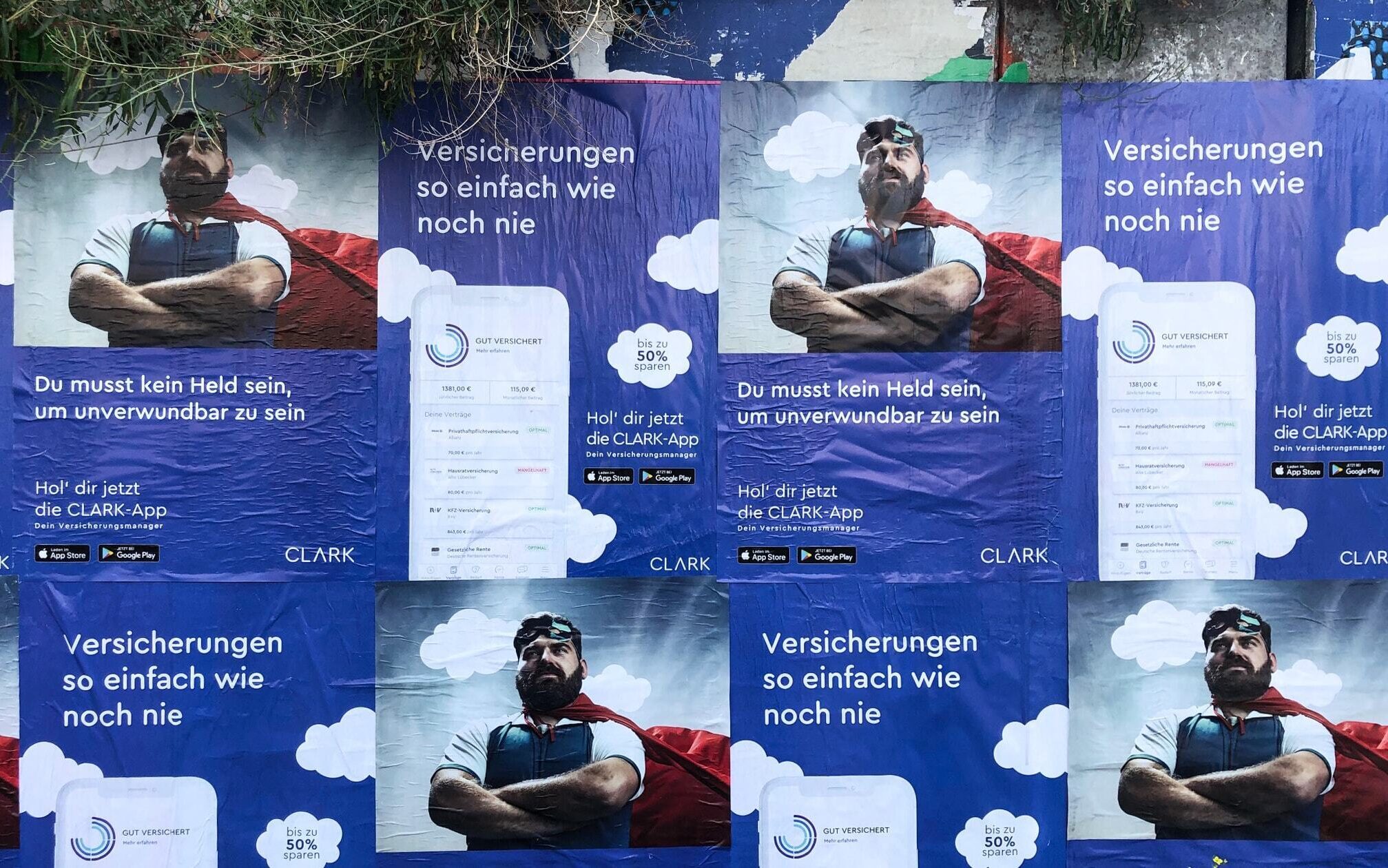
Rundet die Cera Collection ab und bringt Wärme in lateinische, Кириллица und Ελληνικά Sprachen.
Cera Round
CLEAN & FRIENDLY
So gut ausgebaut wie der Rest der Cera Collection, fügt sich die abgerundete Variante Cera Round in die Schriftfamilie ein und verbindet schlichte Eleganz mit einer gewissen Wärme, ergänzt diese jedoch durch weiche und zugleich präzise Formen, welche die Geometrie des kreisrunden Buchstabens O noch einmal verdeutlicht.
In der Tradition von maschinell gefräster Schrift zeichnet sich die Cera Round durch exakt kreisförmige, streng geometrische Strichenden aus. Die Cera Round kombiniert so die mechanisch-technische Geometrie der Cera mit weichen Rundungen, wodurch sie einen sanften, freundlichen Charakter erhält. Eine gute Wahl für Branding und Editorial Design – egal ob für klare High-Tech-Unternehmen oder sanfte Babynahrung.
Durch die Unterstützung der kyrillischen und griechischen Zeichensätze wird die Cera Round zu einem zuverlässigen und einnehmenden Begleiter für internationale Kommunikation. Darüber hinaus ist die große x-Höhe vorteilhaft für Interface Design.
Während der Regular-Schnitt für längere Fließtexte geprüft wurde, bieten die sechs übersichtlichen, aber erkennbar unterschiedlichen Gewichte von Thin bis Black und deren kursiven Stilen, viele Möglichkeiten für die Headline Typografie.
Obgleich die Cera Round als ein Gegenstück der Cera Pro gesehen werden kann, ist sie nicht nur eine simple Version mit abgerundeten Buchstaben. Vielmehr wurden etliche Glyphen sorgfältig neu gezeichnet, um sie an den neuen weichen und dennoch geometrischen Charakter anzupassen. Auch wurde präzise darauf geachtet, die Lesbarkeit in all ihren abgerundeten Ausprägungen zu erhalten. So kann sich die Cera Round als eigenständiges Mitglied innerhalb der Cera Collection behaupten. 2021 haben wir die Familie um die Kursive erweitert, um Cera Round noch ein etwas vielseitiger einsetzbar zu machen.
Ferner enthält die Cera Round viele typografische Extras wie Tabellenziffern, automatische Brüche, nützliche Symbole und Dingbats. Darüber hinaus unterstützt die Cera Round nicht nur die lateinischen Sprachen, sondern beinhaltet auch griechische und kyrillische Zeichensätze mit sprachspezifischen Alternativformen, welche in Zusammenarbeit mit einheimischen Beratern entwickelt wurden. Mit mehr als 900 Glyphen pro Schnitt unterstützt die Schrift auch sprachspezifische Buchstabenvarianten und bietet die passenden OpenType Features.
Die paneuropäische Cera Collection ist von purer Geometrie geprägt und umfasst den Bestseller Cera Pro, ihre platzsparenden Condensed Schnitte, die Schablonenschrift Cera Stencil sowie die handgefertigte Display-Variante Cera Brush und die weiche Cera Round.
Design von
Jakob Runge, Lisa Fischbach
2016, Italics 2021
Irene Vlachou, Ilya Ruderman & Yury Ostromentsky, Christoph Koeberlin
Griechisch: monotonisches Griechisch
Alle enthaltenen OpenType-Funktionen: Alternativen für die Auswahl, Brüche, Durchgestrichene Null, Glyphenz-Zusammensetzung/Zerlegung, Hochgestellt, Kerning, Kontextbedingte Alternativen, Markierung zu Markierung Positionierung, Minuskelziffern, Nenner, Ordinalzeichen, Proportionale Ziffern, Sprachabhängige Formen, Stilistische Alternativen, Stilistisches Set: Alternatives Ξ, Stilistisches Set: Bulgarische kyrillische Alternativen, Stilistisches Set: Dreieckiges ЛлДд, Stilistisches Set: Geometrische Alternativen, Stilistisches Set: Geometrisches a, Stilistisches Set: Geometrisches y, Stilistisches Set: Marcedonische kyrillische Alternativen, Stilistisches Set: Rundes ξ, Stilistisches Set: Rundes ф, Stilistisches Set: Serbische kyrillische Alternativen, Stilistisches Set: Tabellarisches Set, Stilistisches Set: Ziffern eingekreist schwarz, Tabellenziffern, Tiefgestellt, Versalformen, Versalziffern, Wissenschaftliche tiefgestellte Ziffern, Zähler